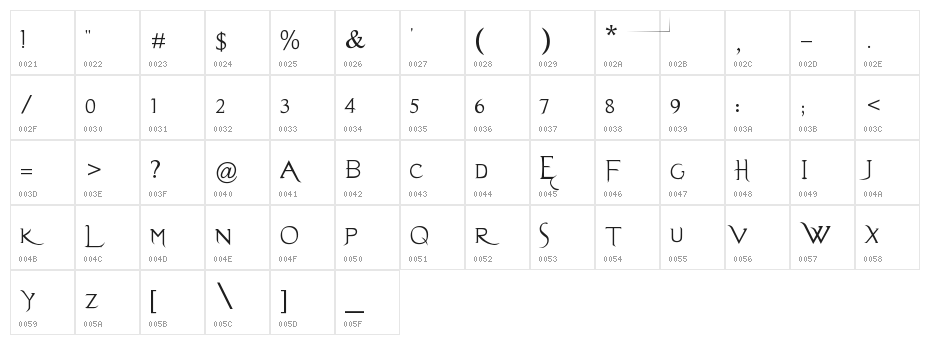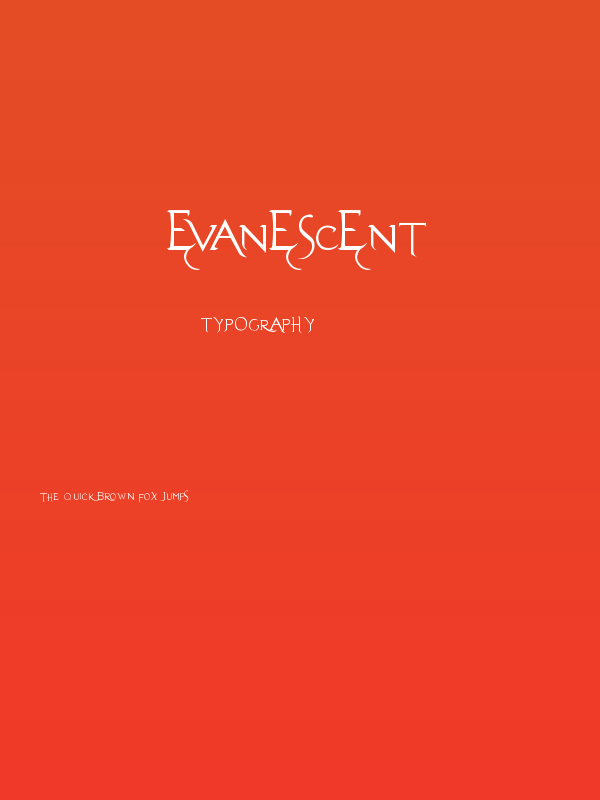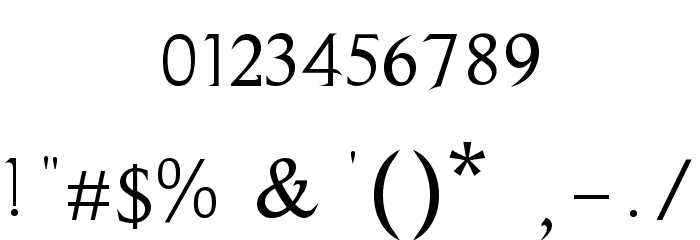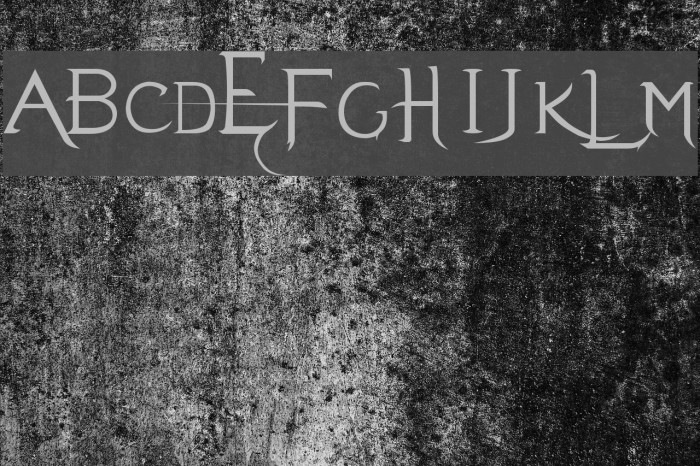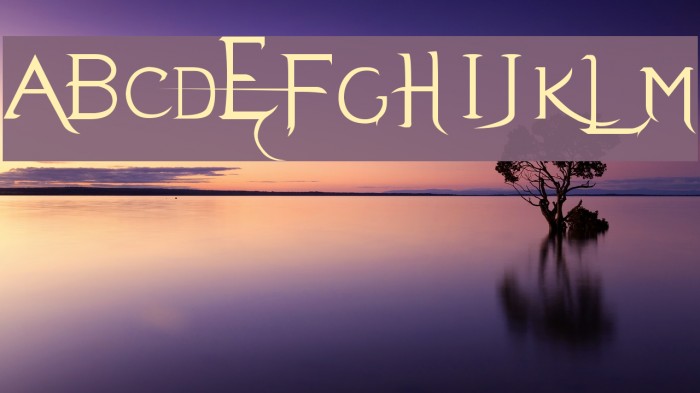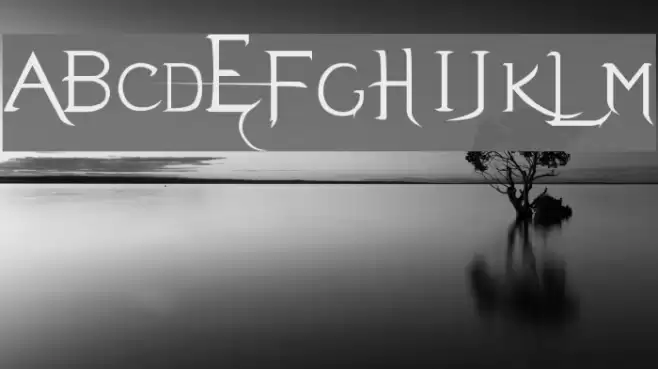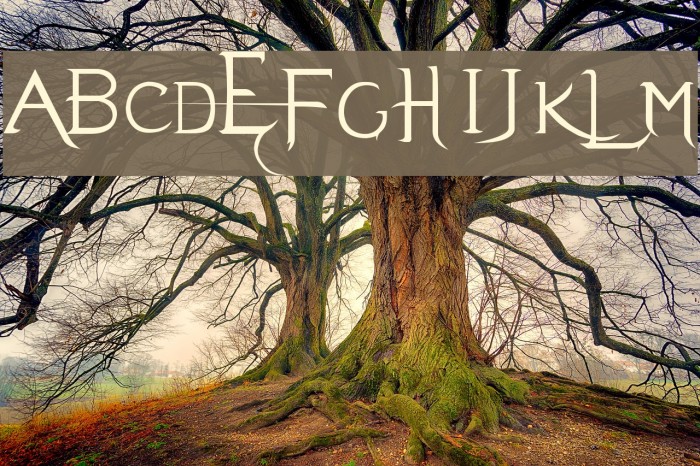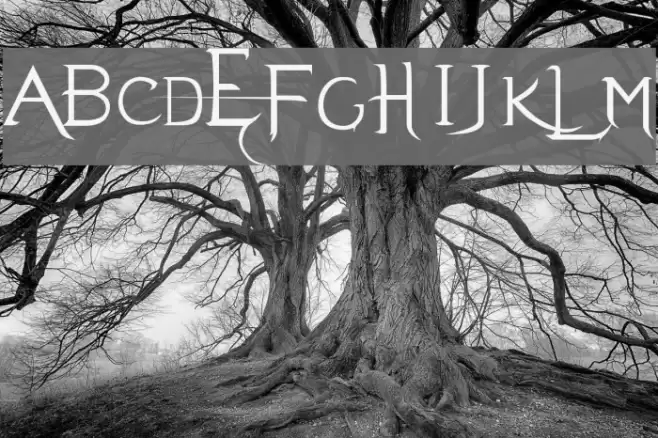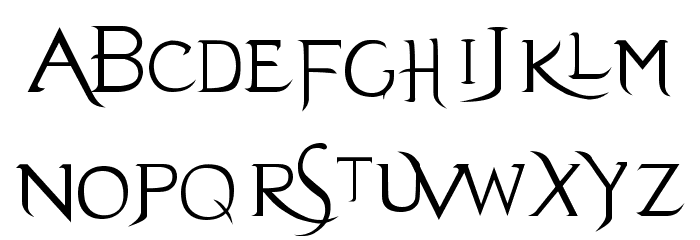
Evanescent Font
| Proiecte propuse | Ideal for book covers, fantasy-themed designs, elegant invitations, and branding that requires a touch of sophistication. |